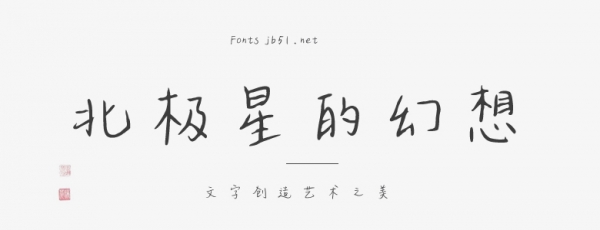
北極星的幻想,這款字在構(gòu)字方式上,部件的設(shè)計(jì)往往出人意表,部件間的組合方式頗有新意,最終又能使字形具有別樣的觀賞性和趣味性。是一款創(chuàng)新意識(shí)很強(qiáng)的字體。適用于文化類的宣傳設(shè)計(jì),以及商業(yè)類品牌的廣告和產(chǎn)品包裝設(shè)計(jì)。